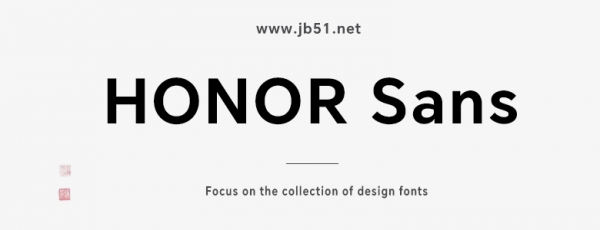
榮耀字體HONOR Sans是業(yè)界首款支持字重和中宮雙重無極可變的字體,將榮耀字體與 UI 融合,通過間距優(yōu)化,讓排版更整齊,適合應用于藝術(shù)設(shè)計、平面宣傳設(shè)計、網(wǎng)頁設(shè)計,書法字帖等領(lǐng)域,需要的朋友可以前來本站下載。
字體介紹
榮耀帶來了全新的 HONOR Sans 字體,號稱是業(yè)界首款支持字重和中宮雙重無極可變的字體,將榮耀字體與 UI 融合,通過間距優(yōu)化,讓排版更整齊,層次更清晰。
榮耀將其稱為”會呼吸的字體“。HONOR Sans 將面向全社會免費授權(quán)開放,覆蓋全場景全人群使用,而且未來也將推送到榮耀全場景設(shè)備上。